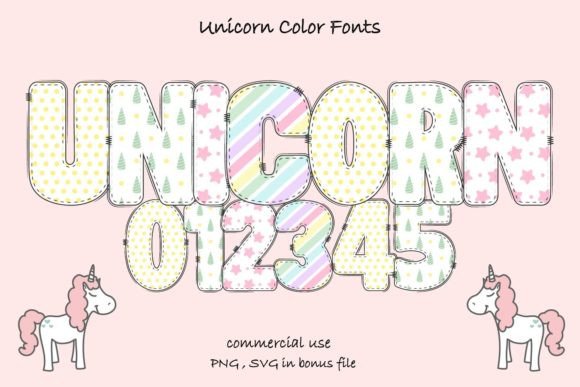
Unicorn
Encontrar los elementos de diseño adecuados puede ser un desafío, pero Unicorn ofrece una colección excepcional que eleva tu trabajo al instante.
Elaborado con precisión, Unicorn proporciona vectores limpios, tipografía suave y una licencia comercial para tu tranquilidad.